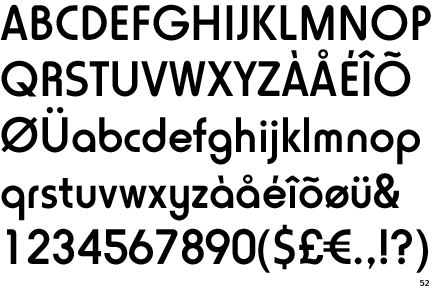
Suche eine passende Schrift zur Horatio
Ich hab hier ein Logo, dass mit der Horatio erstellt ist.
Nun brauch ich für den Fließtext ne gut lesbare Schrift, die zum Schriftbild der Horatio passt. Irgendwie find ich da keinen. Hat da jemand eine Idee. Wäre sehr dankbar für einen Tipp.
Es wird eine Broschüre und da soll halt einiges an Infotext rein.
Es handelt sich um eine Baufirma.
Seriös und kompetent soll die Schrift wirken. Bei der Firma handelt es sich um eine Firma, die bereits länger als 10 Jahre auf dem Markt ist. Also schon etwas traditioneller ist.
Seriös und kompetent
aber HORATIO im logo :lol:
was würdest du nehmen? oder was steht dir zu verfügung.
da könnte man echt so viel nehmen, von univers über avenir, akzidenz gotesk, myriad bis zu meta und unit.
ok. das ist schonmal was, wenn auch nicht viel.
soll es eine serifenschrift oder eine sans sein?
kannst du auf einen fundus zurückgreifen, bzw. hast du schon etwas im auge?
was wurde vorher genutzt?
hast du dir die diversen größe wie z. b. die frutiger schon angesehen?
Also ich hab nen relativ großen Fundus und zur Not wird die Schrift gekauft. Welche vorher benutzt wurde. Nun ja, das haben immer wieder unterschiedliche Agenturen gemacht und CD war da nicht wirklich ein Begriff. Ob Serifen oder Sans ist "eigentlich" egal. Gut, ich weiß, die Horatio ist leider nicht die schönste Logoschrift, aber damit muss man jetzt leben. Leider sind das nun keine wirklichen Einschränkungen.
Nein, eine genaue Vorgabe habe ich nicht und eine Auswahl habe ich persönlich auch noch nicht getroffen. Sonst könnte man ja eine Schriftmischung machen. Z.B. für die Headline eine Sans und für den Infotext eine Serifenschrift. Avenir z.B. gefällt mir ganz gut. Oder wird das zuviel, wenn in dem Logo auch noch die Horatio genommen wird. Aber ich möchte die eigentlich nicht im Text sonst verwenden.
horatio würde ich nicht im text verwenden, nicht nur deshalb weil es deine
logoschrift ist, sonfern weil es ja 'seriös' wirken soll. avenir finde ich eine
gute wahl und könnte ich mir sehr gut vorstellen. vielleicht sogar avenir next.
Hättet ihr dann auch noch nen Vorschlag für den Fließtext. Am Besten wäre eine Serifenschrift.
Also, da die HORATION nicht wirklich mit irgendeiner Serifenschrift
»harmoniert« im Sinne des gleichen Formenprinzips, würde ich sagen,
dass man zu viele Serifenschriften zur Auswahl hätte, die einen Kontrast
zu HARATIO bilden, als dass man Dir nun eine besonders ans Herz legen könnte.